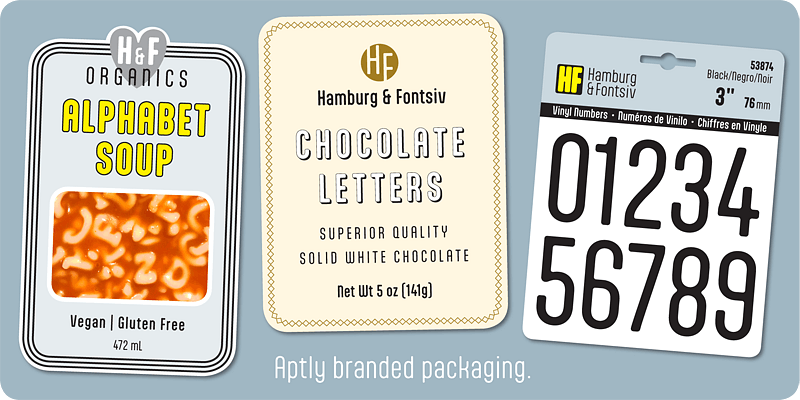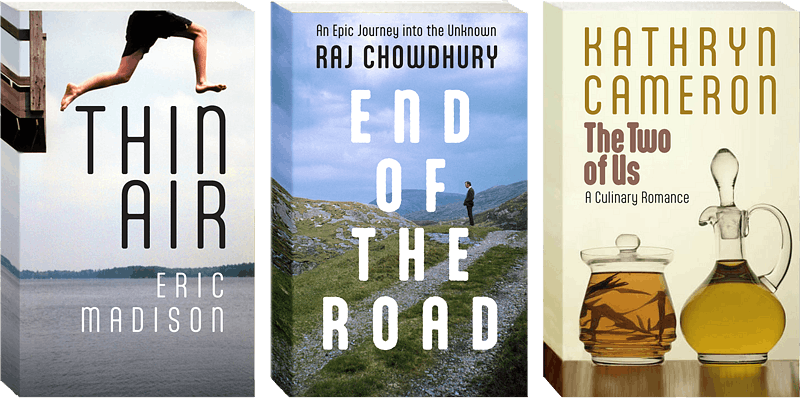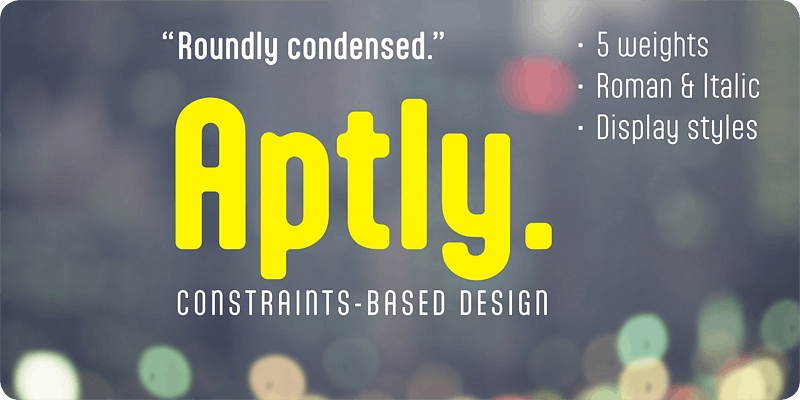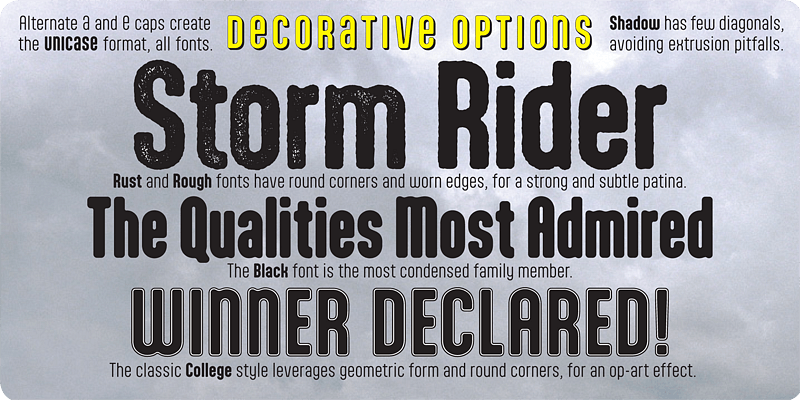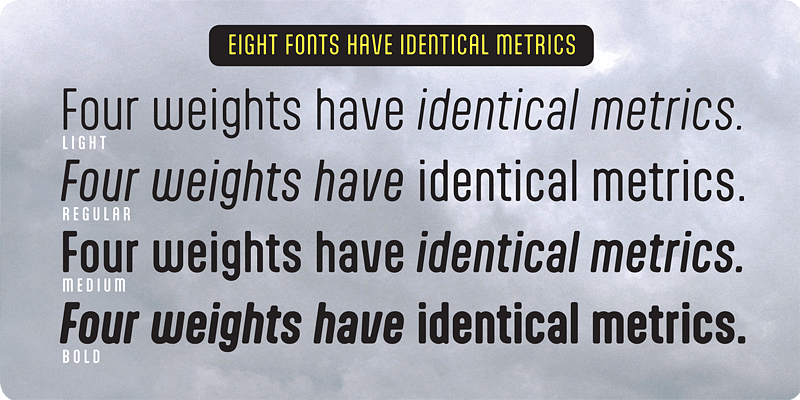
Als grenzgängerisches Werk nimmt Aptly die normalisierenden Beschränkungen technokratischer Systeme in den Blick. Dazu präsentiert sich der Design-Raum von Aptly als Matrix strenger Einschränkungen, die eine ästhetische Auflösung fordern. Das Lösungskonzept heißt „Geo-Soft“, Buchstaben, die fast ausschließlich aus Kreisbogen, verbindenden rechtwinkligen geraden Linien und kaum spitzen Ecken konstruiert sind – als würden Wörter durch eine Festmaßdimension geleitet. Die Wirkung ist die einer anziehenden Spannung, weiche Kanten im Kontrast zur strengen Struktur, Wörter, die gleichzeitig schmelzen und aufgereiht werden. Aus dieser abstrakten Vorlage erschafft Shinn eine kühle, elementare und zeitlose Ruhe.